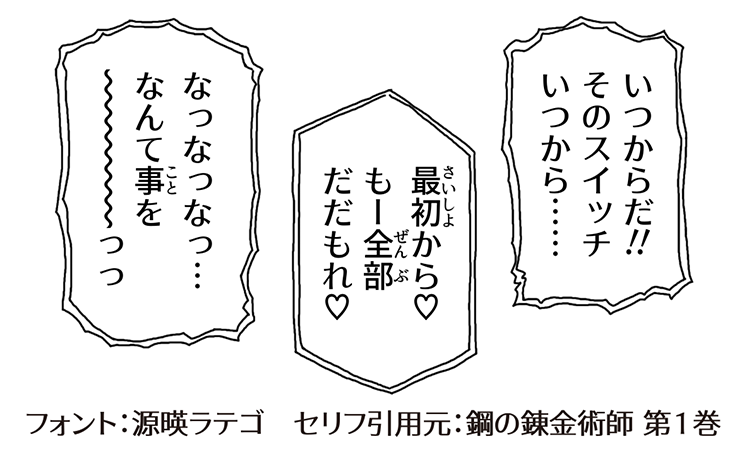
源暎ラテゴは、放送音声などによく用いられる、ラテン体のフリーフォントです。フリーフォントとしては珍しい、いわゆるタイポス系のフォントです。ゴシック体と明朝体、両方の雰囲気を合わせ持った独特なフォントは、ロゴやテロップなどで大きなサイズでもスッキリと使うことができます。普通のゴシック体と、横細・縦太な仮名の組み合わせです。
このタイプのフォントとしては、有償の「ComicStudio-GT」が有名ですが、こちらのフォントは現在では入手が困難な状況で、一般的に使えるフォントの中に有用な選択肢がありませんでした。
源暎ラテゴは「源暎ゴシック」の2種類のウェイト、Light とSemibold を下地に作成されており、使い勝手のいい仕上がりです。骨格は源暎ゴシックがベースになっているので、漫画のセリフ部分に源ノ角ゴシック、源真ゴシック、源暎ゴシックを一緒に使っても、全体として違和感がありません。
源暎ラテゴと源暎ラテミン
メインでの使用は源暎ラテゴです。源暎ラテミンは、漢字をラテン体風に加工したおまけフォントです。仮名の作風に合わせて、源暎ゴシック Lightの漢字を横太に処理してあります。ロゴやキャッチコピーなど、大きなサイズで使用する際に、源暎ラテゴでは仮名と漢字の作風の違いが違和感の元になってしまうことがあります。そんなとき、源暎ラテミンならば漢字の作風を仮名に合わせてあるので、違和感なく使用することができます。
欧文には、どちらも「Linux Biolinum」を調整したものが使われています。